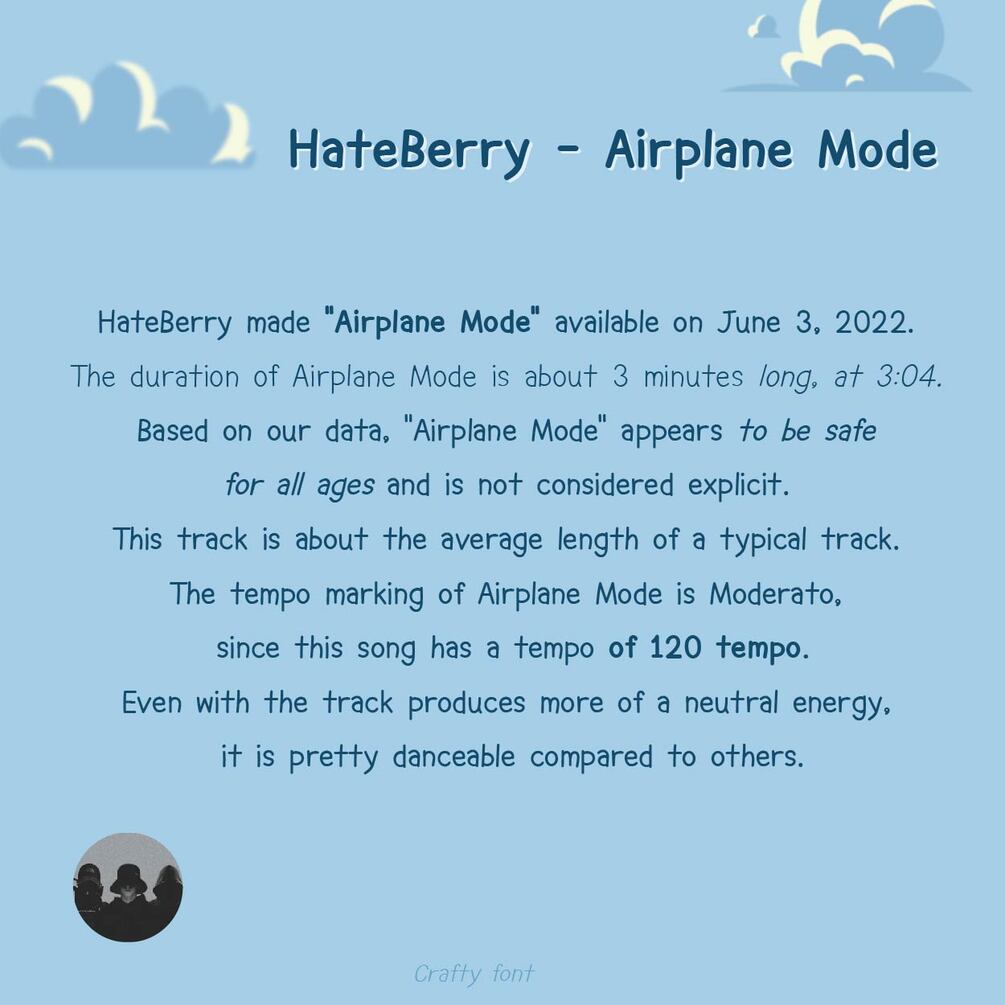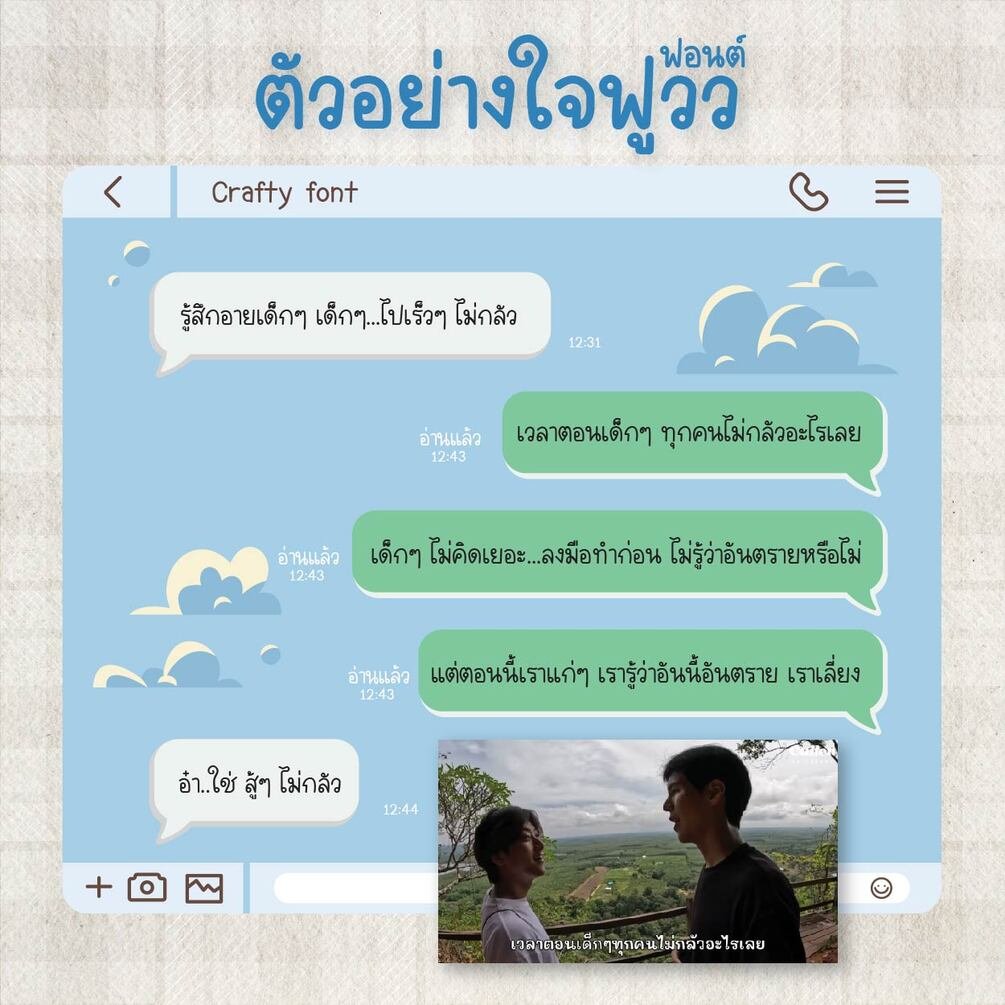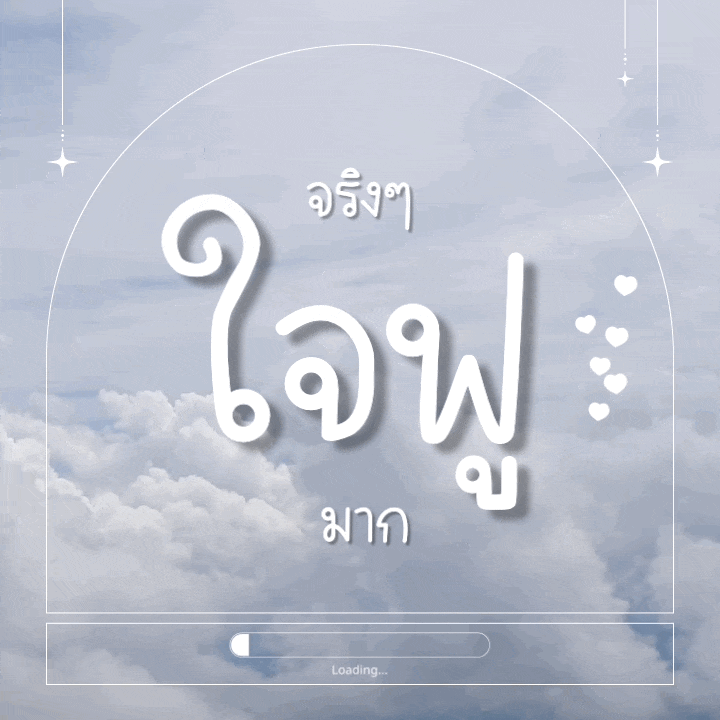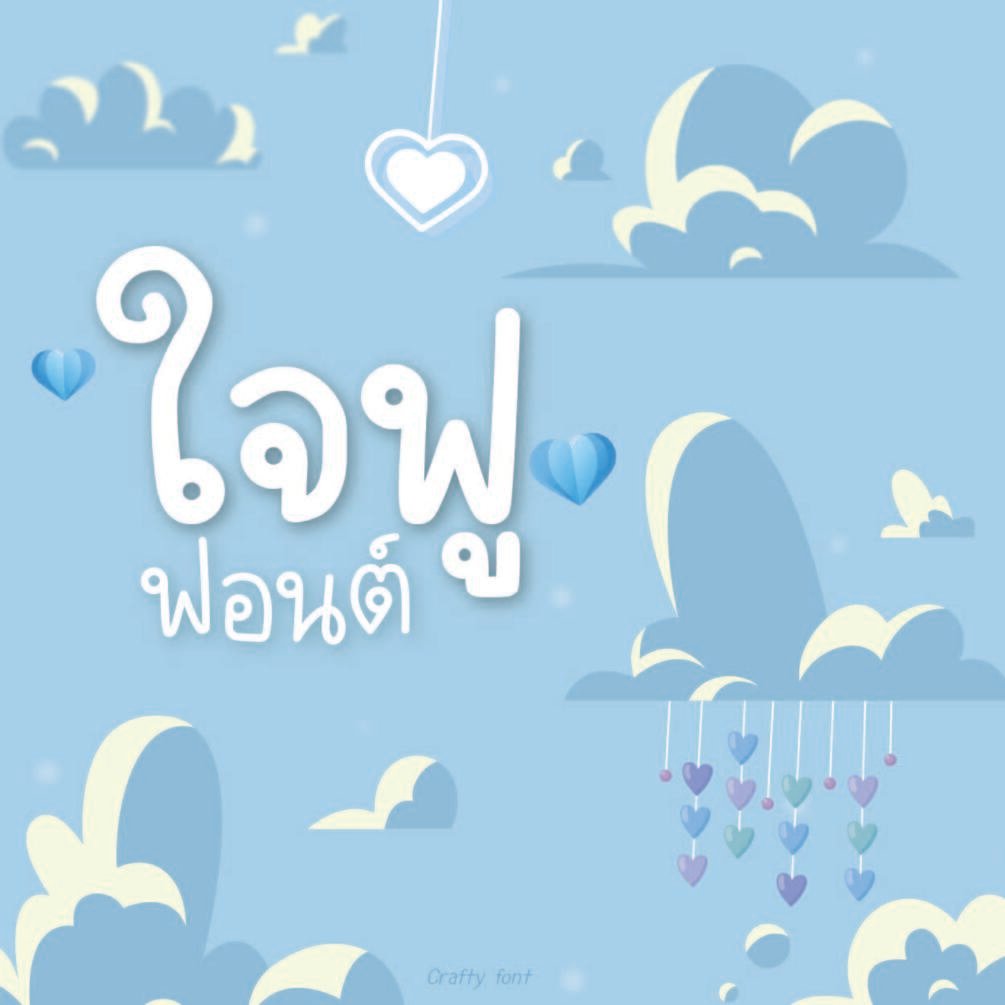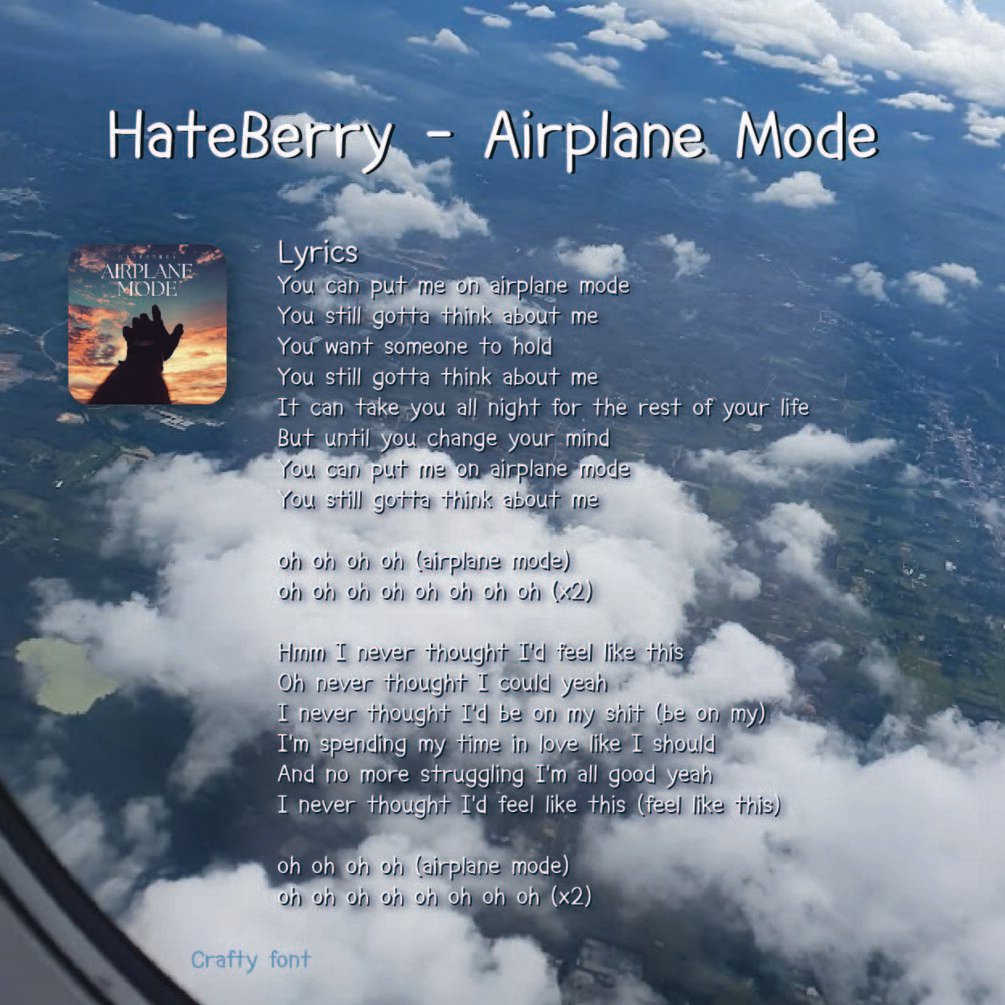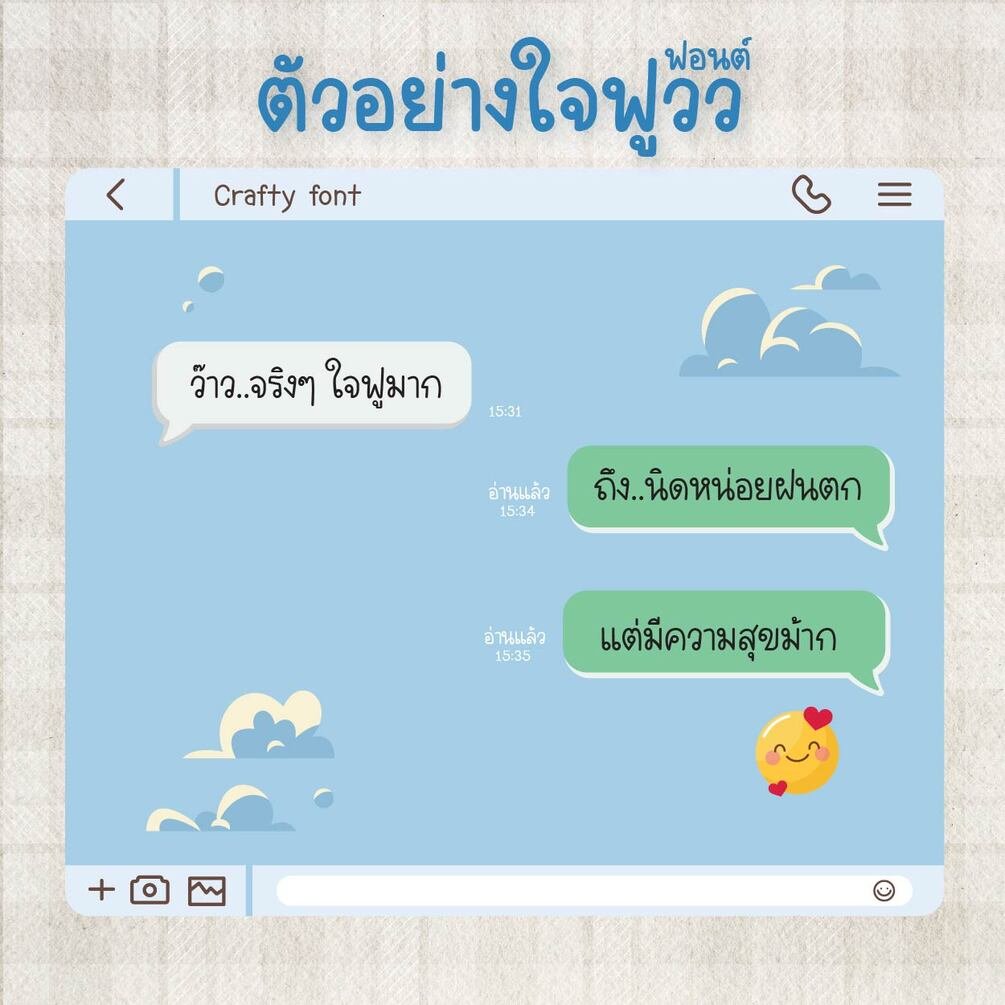
Jaifu Font (ฟอนต์ใจฟู)
ฟอนต์ใจฟูวววว นั่งฟังเพลง Airplane Mode - HateBerry แล้วรู้สึกมีความสุข 🤗 เลยตั้งใจเขียนให้ตัวอักษรมีความลอยๆ เหมือนปุยเมฆ เลือกใช้เส้นปากกาแบบสมูทน่ารักนุบนิบ ไม่ทางการ มีความขี้เล่นในบางตัว เพื่อเวลาพิมพ์จะได้ไม่ทางการจนเกินไป และจะได้ใช้ในทุกโอกาส หวังว่าทุกคนจะชอบนะคะ ❤️ 💞🙏🏼